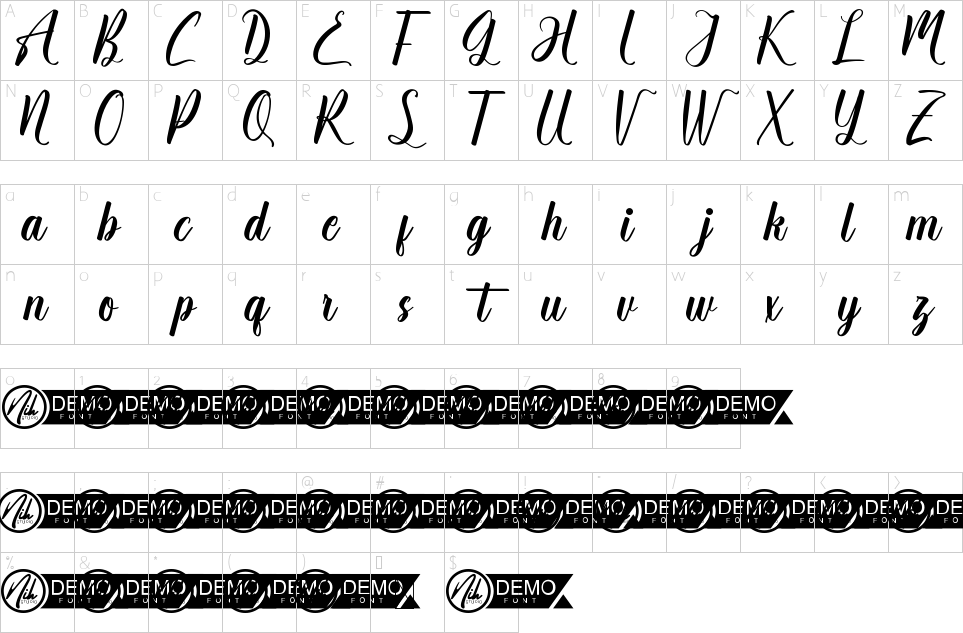
A fonte ‘Mark Hayes Font | 1001 Free Fonts’ é uma excelente opção para designers gráficos que procuram uma fonte com estilo. Desenhada pelo designer nihstudio, esta font oferece um design elegante e elegante que se destaca em qualquer projeto. Ela foi projetada para se adaptar perfeitamente a textos do cotidiano, desde pequenos detalhes até grandes títulos. Com seu design minimalista e com uma vasta gama de usos, a font ‘Mark Hayes’ é um ótimo complemento para os criadores de materiais gráficos, proporcionando um visual moderno e moderno a seus projetos. Para quem está procurando por opções de fontes gratuitas, esta é uma excelente escolha. A font ‘Mark Hayes’ é uma opção versátil e agradável que se integra perfeitamente em qualquer design.